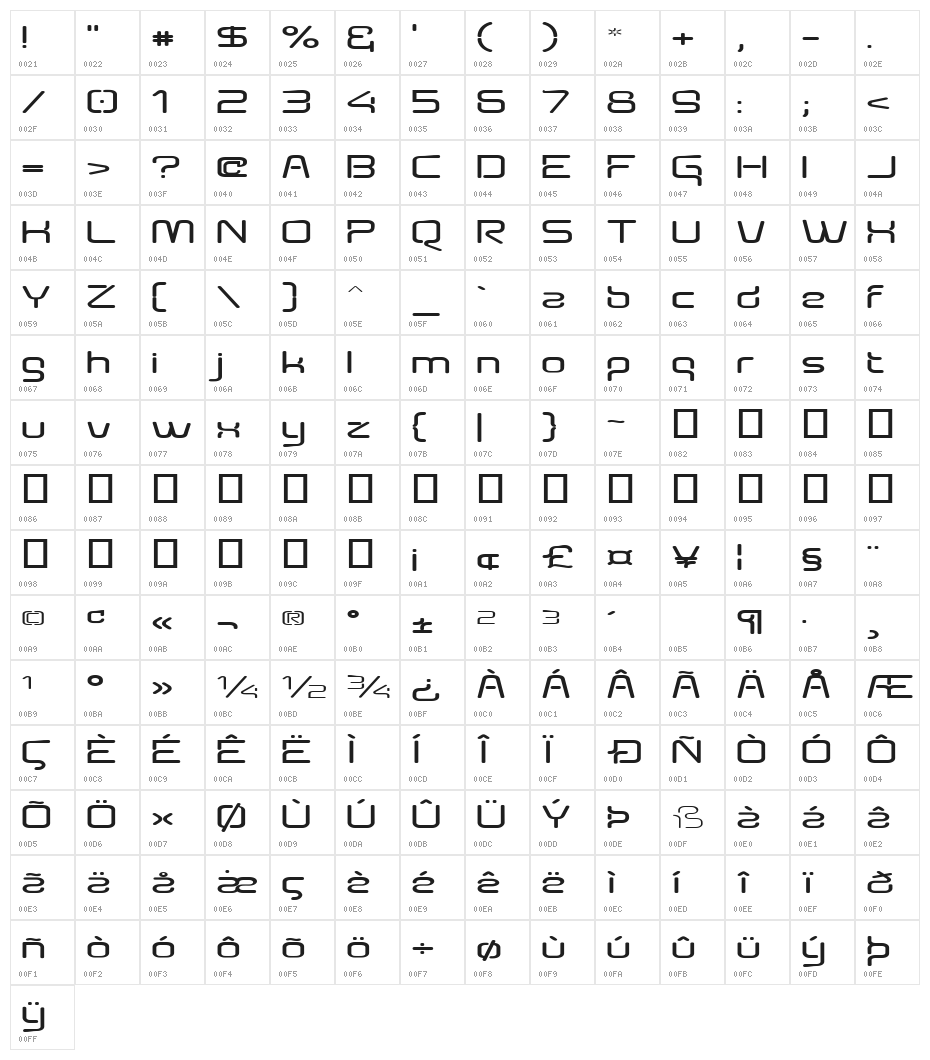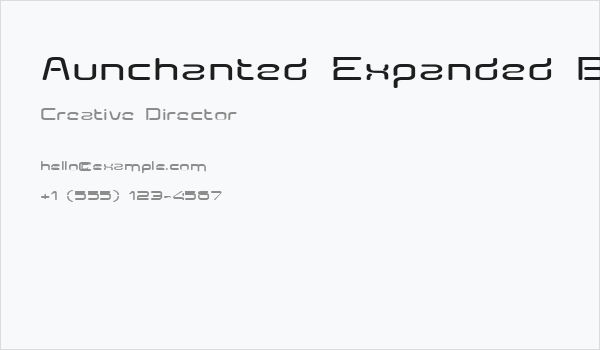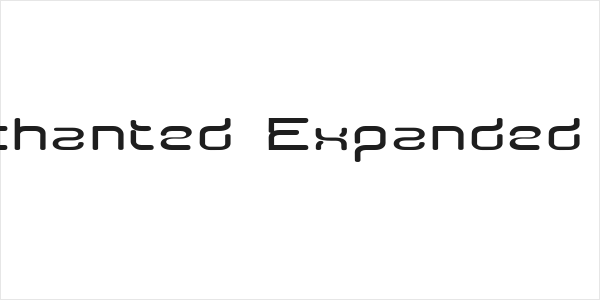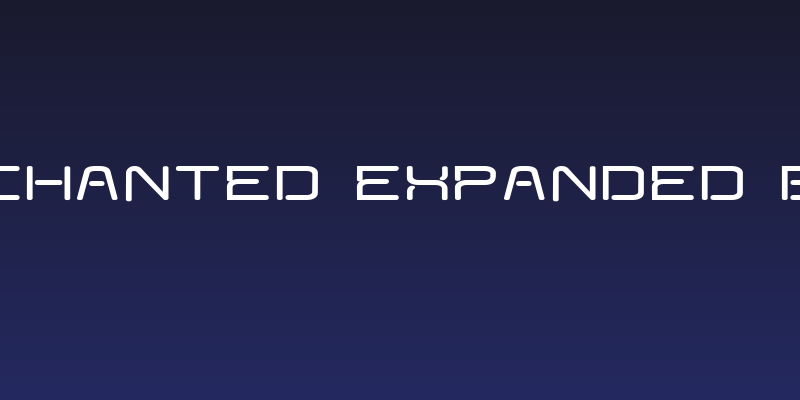
Aunchanted Expanded Bold Font
✎ Futuristic
| Kategorien | Futuristic |
| Breite | Expanded |
| Anwendungsfall | Headlines, Logos, Branding |
| Vorgeschlagene Projekte | Ideal for technology branding, sci-fi posters, modern web design, and innovative product packaging. |